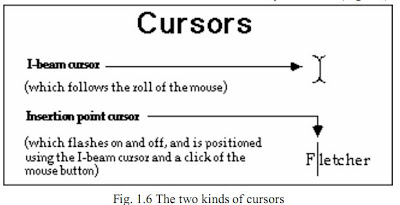
Winkelhaken / composing stick = Ursprung der Text-Eingabemarke (i-beam cursor)?
ich wüßte gerne, was der Ursprung des Symbols der Text-Eingabemarke (heißt das so?) ist. Im Englischen wird dieses Symbol anscheinend i-beam cursor bezeichnet?
Hier ein Bild davon:
Ein Bekannter meinte, es käme von den Winkelhaken (Frosch), die früher von den Schriftsetzern im Bleiletterndruck verwendet wurden.
Wer weiß hierzu Näheres?
Das es vom Winkelhaken kommt, glaube ich eher weniger, denn  der verstellbare Frosch war ja eher mit der Einstellung des rechten Seitenrandes zu vergleichen, als mit der Eingabemarke.
Ich glaube mehr, dass die Eingabemarken-Cursor eher ihren Ursprung in Korrekturzeichen nach DIN 16511 haben.
Na eine deutsche Erfindung war das wahrscheinlich nicht.
Es würde mich nicht wundern, wenn es dazu überhaupt keine besondere Erklärung gibt. Die frühen Monitor-Textdarstellungen waren einfach und rasterbasiert. So eine Pixellinie mit deutlichen Serifen ist da eine nachvollziehbare Lösung.
Aber jedenfalls eine interessante Frage! :-)